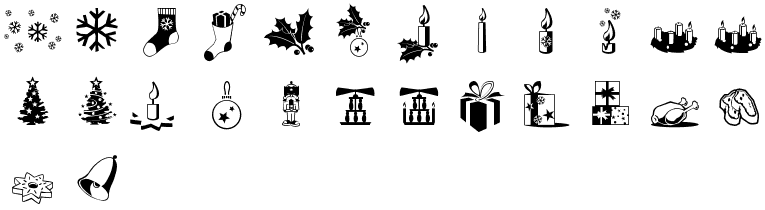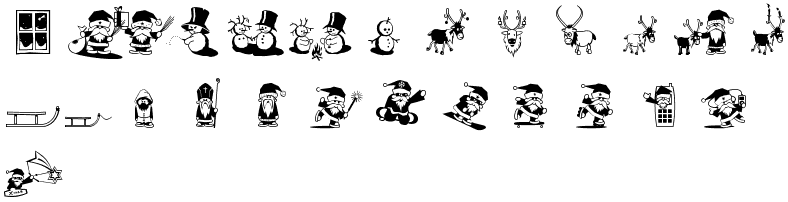
東京はだんだん寒くなってきました。10月は雨ばっかりだったので、11月は晴れて欲しいですね。そろそろクリスマスカードや年賀状の準備をしなければいけないですね。1年を通して思い出に残った写真をカードにして送りたいな〜と思ってるのですが・・・迷ってしまいそうです。毎年海外の友達からは、12月上旬になるとカードやプレゼントが届いてしまうので、今年こそ早目に送りたいと思ってるのですが、いつもバタバタ遅れ状態です。今月はクリスマスカードを作ったりするのにピッタリの新フォントを紹介してるので、是非参考にしてみて下さい。
あちらこちらで街頭ツリー点灯のニュースをみたりすると、いよいよクリスマスが近づいてるなという感じですね。Linotype Xmas フォントも待ちきれないといった感じです。うっとり〜眺めたり、フレンドリーな楽しい感じで幅広く使用できる書体をドイツ Fuenfwerken Design スタジオより、自信を持って最新のファンフォントをご紹介致します!色んな種類のブランククリスマスカードや休日家でするパーティ用のポスターなどで使用するのも良し、あなたの創造性を思いっきり使って楽しめるフォントです。
このファミリーは、3種類の書体を用意しています。それぞれ60個以上ものシンボルを取り揃えています。Xmas Story フォントには、昔ならではのクラシックなクリスマス物語(聖書的な)に必要なシンボルを用意しています。年配の方へのお手紙にも使えそうな可愛い赤ちゃん(イエス)、3人の東方の三博士、アラム羊で飾りつけたり、子供達に家でのキリスト降誕劇 をやったりするにも最適です。
もし聖書っぽくないフォントを探しているのなら Xmas Essentials フォントがお勧めです。Essentials のウェイトには、クリスマスに必要な雪の結晶、クリスマスツリー、ナッツクラッカー、星といった典型的な無宗派的な書体を揃えています。又、1年を終える休日の装飾書体も充実しています。
最後に忘れてはいけないのがモダンフォントです。Xmas Morden フォントは、地球温暖化が雪だるまに危険をさらしている深刻な問題を訴えてるような書体もありますが、休日やニューイヤーカードを受取れる側にとっては、心を溶かしてくれるような暖かい感じの書体ばかりが揃っています。ベスパに乗ったサンタクロースが iPod を聞いてたり、携帯からサンタさんが顔を出してたりと息苦しいイヤ〜な休日をどっかに吹き飛ばしてくれる楽しいお茶目な書体から一般的なシンプルで可愛い雪だるまやサンタクロースフォントも多く収録しています。
勿論1番良いチョイスは、この3つのクリスマスフォントを揃えて同時に使い、皆さんの思い描く何かを作れればいいと思います。来月にはやってくるクリスマスとお正月に今から準備を始めましょう。きっと素敵な日を迎えられるでしょう!
Xmas™ Story
Xmas™ Essentials
Xmas™ Morden